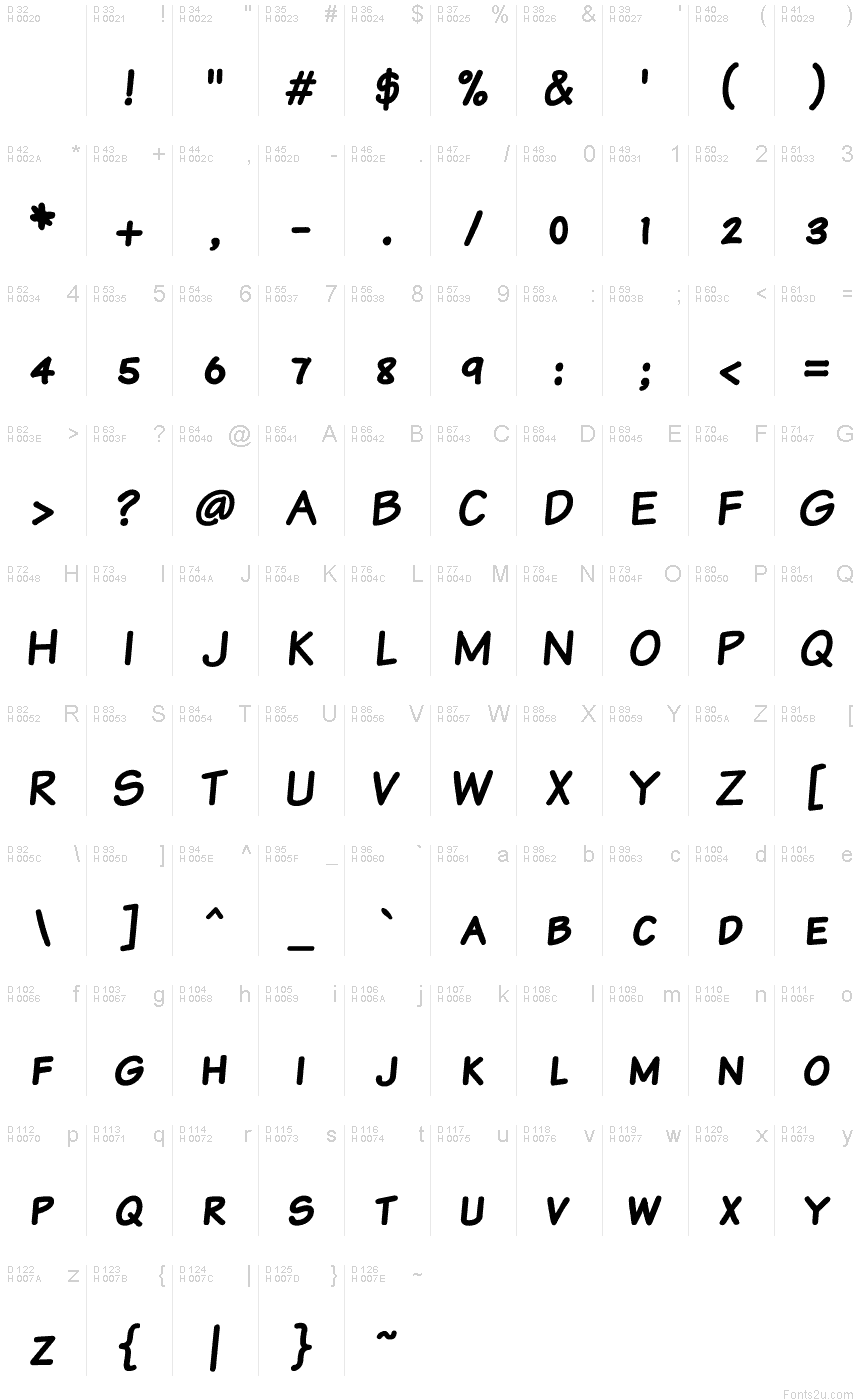
Krój pisma Komika Text Kaps Bold autorstwa Wolfbainx & Apostrophic Labs to darmowy, komiksowy font, który idealnie łączy w sobie zabawny charakter z czytelnością. Masywne, miękko zaokrąglone litery przypominają pewne pociągnięcia mazakiem, a dzięki ciasnemu i równemu kerningowi tekst pozostaje przejrzysty i łatwy w odbiorze. Oferuje komiksową energię bez efektu drżenia, co czyni go świetnym wyborem, gdy potrzebujesz przyjaznych, wyrazistych nagłówków, które czyta się błyskawicznie.
Komika Text Kaps Bold doda charakteru Twoim webkomiksom, dymkom dialogowym, plakatom, grafikom do mediów społecznościowych, naklejkom czy nakładkom w grach. Ten darmowy font świetnie wygląda w dużych rozmiarach, a jednocześnie pozostaje czytelny w krótkich podtytułach. W przypadku dłuższych treści połącz go z prostym, lżejszym bezszeryfowym krojem – niech Komika Text Kaps Bold przejmie na siebie rolę elementu, który przyciąga uwagę.